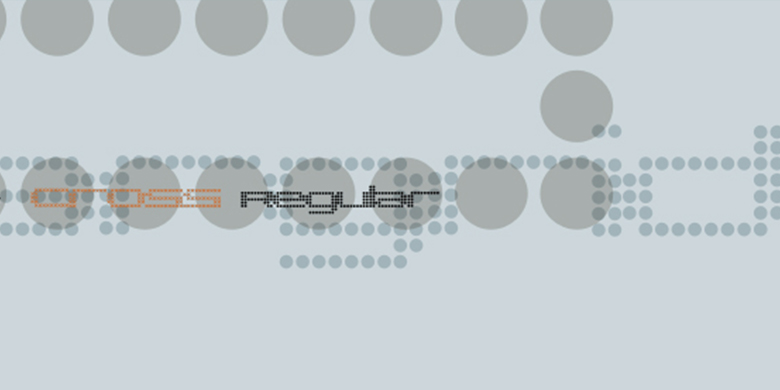
Pargrid™
Pargrid是年轻的瑞士设计师Michael Parson设计的一款基于网格的字体设计。Pargrid家族包含三个独立的字重,Parson创作了一个有趣的小圆环系统——类似于LED或灯泡——它们分别位于一个网格上,创作了独特的字体。在小尺寸中,这些圆圈混合在一起,创作出看似流畅的线条,使Pargrid的字母呈现出宽阔的矩形外观。在更大的尺寸中,这些字体将自己转化为艺术对象——由不同的点组成的虚拟有序的团体。无论是显示设置还是短字符串文本,Pargrid都可以提供您下一个项目所需要的精确外观。Linotype GmbH的Take Type 5家族中包括Pargrid和其他来自Parson的九种结构化字体设计。
Pargrid is a grid-based typographic experiment from the young Swiss designer Michael Parson. In the Pargrid family, which contains three separate weights, Parson has created an intriguing system of small circles-similar to LED's or light bulbs-that live separately on a grid, creating unique letterforms. In small sizes, these circles blend together to create seemingly fluid lines, giving Pargrid's letters a wide, rectangular appearance. In larger sizes, the letterforms transform themselves into objects d'art-virtual and ordered communities populated by various points. Fantastic in both display settings as well as short strings of text, Pargrid may offer the exact look that your next project is looking for. Pargrid and nine other constructed type designs from Parson are included in Take Type 5 collection, from Linotype GmbH."